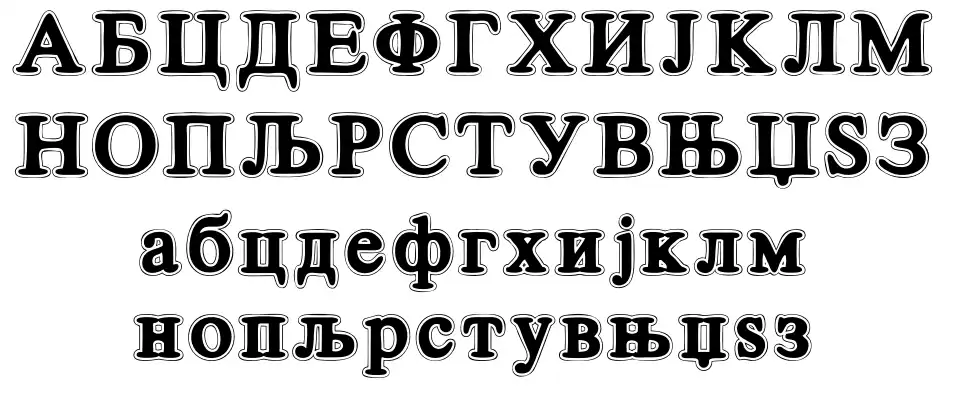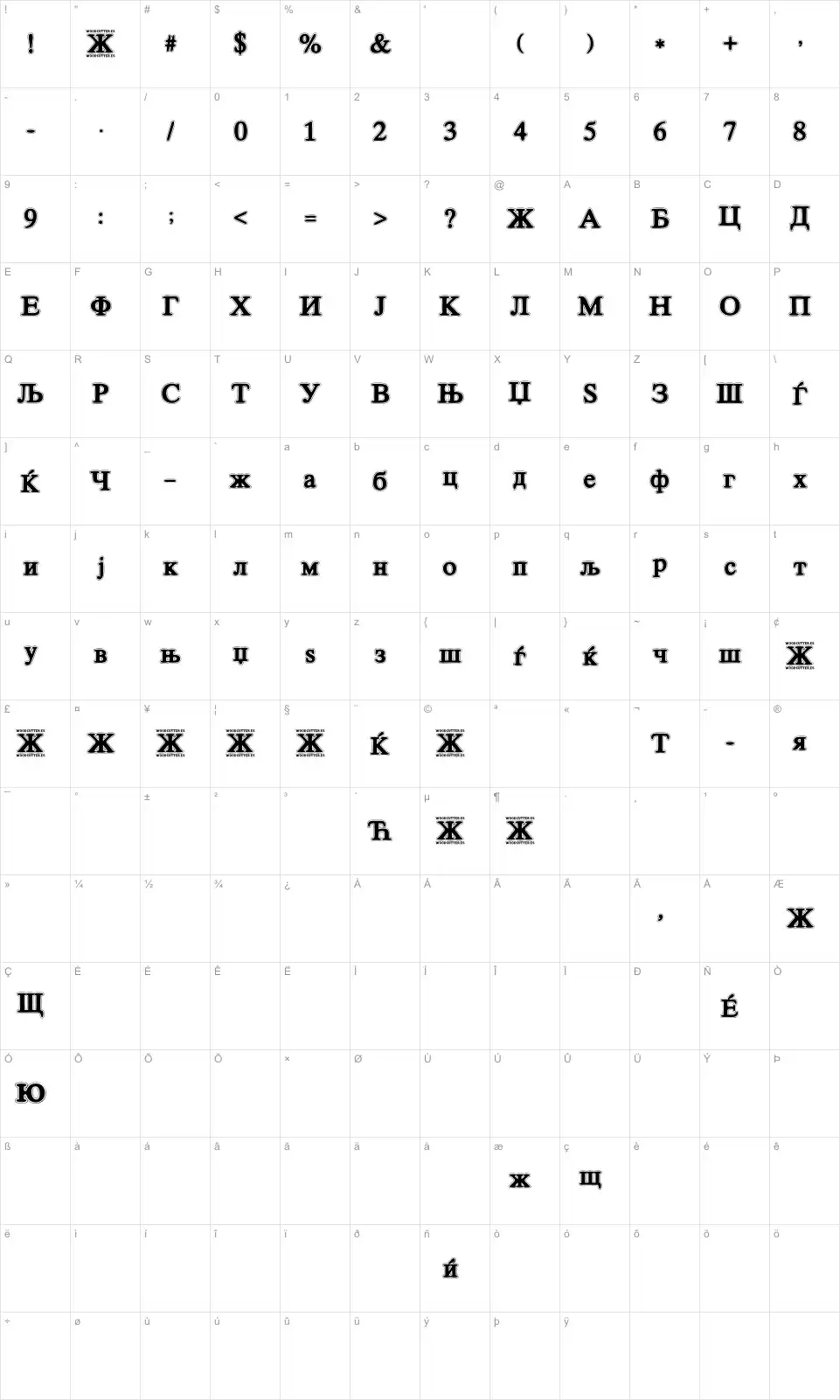
Cirilico Font – Download Grátis
A fonte Cirilico Font, criada pelo designer Woodcutter, é perfeita para quem busca uma fonte estrangeira com um tom russo. Ela faz parte da categoria Foreign Look, uma seleção de fontes estrangeiras que traz a riqueza e o encanto de diversas culturas ao seu design. Se você está procurando por uma fonte inovadora para seus projetos gráficos, essa pode ser uma excelente escolha. Com uma licença gratuita, formato TTF e tamanho compacto de 58 KB, a Cirilico Font é simplesmente perfeita para quem busca um estilo moderno e distintivo. Desde 2022-07-12, mais de 4000 pessoas já experimentaram e baixaram essa font, o que mostra sua popularidade e qualidade. Visite o site do designer, https://www.woodcutter.es, para mais detalhes e oportunidades de utilizá-la em seus projetos.